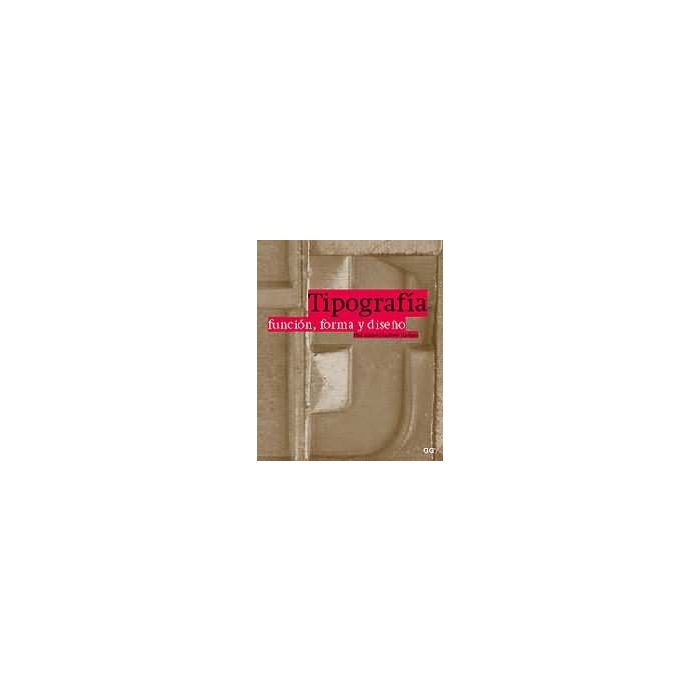
Tipografía. Función, forma y diseño
Un libro de Phil Baines, Andrew Haslam
Este libro proporciona unos conocimientos básicos esenciales a los lectores de cualquier nivel, desde estudiantes hasta profesionales. La tipografía es la notación y organización mecánica del lenguaje que se usa para hacer múltiples copias, ya sea por medios impresos o electrónicos. Su historia en Occidente comienza en 1455, con la publicación de la Biblia de Gutenberg, llamada "de cuarenta y dos líneas", aunque la historia de la escritura y los alfabetos se remonte a miles de años atrás. El libro, cuidadosamente estructurado y profusamente ilustrado, introduce al lector en todos los aspectos clave del tema, desde la historia del lenguaje y la escritura, hasta el invento de los tipos movibles y la evolución de los sistemas digitales actuales. Ofrece una visión de conjunto de la asombrosa variedad de tipos de letra existente y constituye una guía práctica para el uso del tipo como elemento significativo del diseño en todos los medios.
Contenidos: I Definición Introducción ¿Qué es la tipografía? II Función El lenguaje: el sistema oral Otras opiniones El lenguaje: el sistema escrito La gramática El léxico Teorías de la comunicación III Forma Hacia un alfabeto de 26 letras Hacia las letras de caja alta y caja baja Clasificar y describir tipos IV Elaboración y diseño Tipo y rotulación Grabado manual de punzones y tipos de metal movibles Fundición y composición mecánica de tipos de metal movibles Fotocomposición Más allá de lo físico: la composición tipográfica digital Diseñar tipos hoy IV Estructura Planteamientos del diseño Diseñar con tipo en dos dimensiones Desde los diez elementos hasta el diseño unificado La tipografía en el tiempo: el cine y los nuevos medios VI Convenios La estilística del detalle en un texto ... Glosario Bibliografía adicional Cuadro cronológico de diseñadores de tipo Apéndice l: teclado para Macintosh Apéndice 2: teclado para PC Apéndice 3: biografía sucinta de los diseñadores citados en este libro Apéndice 4: tamaños de papel ISO Índice Créditos de las ilustraciones y agradecimientos |
Introducción ( extracto) Desde la llegada de los ordenadores personales, la autoedición y, más recientemente, el desarrollo de internet, millones de personas se han ido habituando a usar fuentes y a trabajar con tipos. Sin embargo, a quienquiera que preguntemos qué es la tipografía, le va a resultar difícil definir cuáles son sus límites o posibilidades. La tipografía se ocupa de estructurar y organizar el lenguaje visual. El diseño de tipos se ocupa de la creación de las unidades que deben organizarse, los caracteres que constituyen un tipo. El diseño de la forma del tipo y la tipografía están encaminados a transmitir un mensaje. Este último aspecto coloca firmemente a la tipografía en la base de una disciplina más amplia, la del diseño gráfico. La cuestión de cómo usar la tipografía para transmitir un mensaje puede subdividirse en dos. La primera parte se ocupa del aspecto o estilo de la tipografía. Éste varía según la época y el lugar, o el diseñador y el cliente; así, en ocasiones, la tipografía juega un papel secundario o hasta invisible, mientras que en otras, su papel es dominante, reflejando la inspiración del diseñador y llegando incluso, a veces, a reclamar su condición de "arte". En este libro mostraremos y debatiremos algunos de esos planteamientos. La segunda parte se refiere a los aspectos prácticos del trabajo tipográfico, como legibilidad, escala y formato, que constituyen la preocupación dominante de esta obra. El libro está concebido en parte para proporcionar buenos consejos a los estudiantes y en parte como una fuente de información concisa, capaz de trascender a la época estudiantil del lector. Inevitablemente, todo libro es un reflejo de los prejuicios de su autor, y el que ahora nos ocupa también refleja nuestra manera de enseñar. Uno de nuestros objetivos es que su ámbito sea amplio, de manera que en un solo volumen se reúna una información que actualmente está dispersa en muchos libros. Aspiramos a proporcionar consejo práctico de una manera abierta, no dogmática. Quizá, lo único que pedimos al lector es que lea nuestro libro, pase a conocer otros escritos sobre la materia y, después, saque sus propias conclusiones. Le advertimos de que este libro también incluye mucha información "objetiva", y no tiene porqué necesitarla toda a la vez. Hemos subdividido el libro en capítulos específicos que pueden ser leídos y comprendidos de forma independiente y a medida que vaya siendo preciso. En muchos lugares, se ha optado por separar el detalle del texto principal, presentándolo a la manera de "episodios laterales" que pueden ser leídos independientemente. |